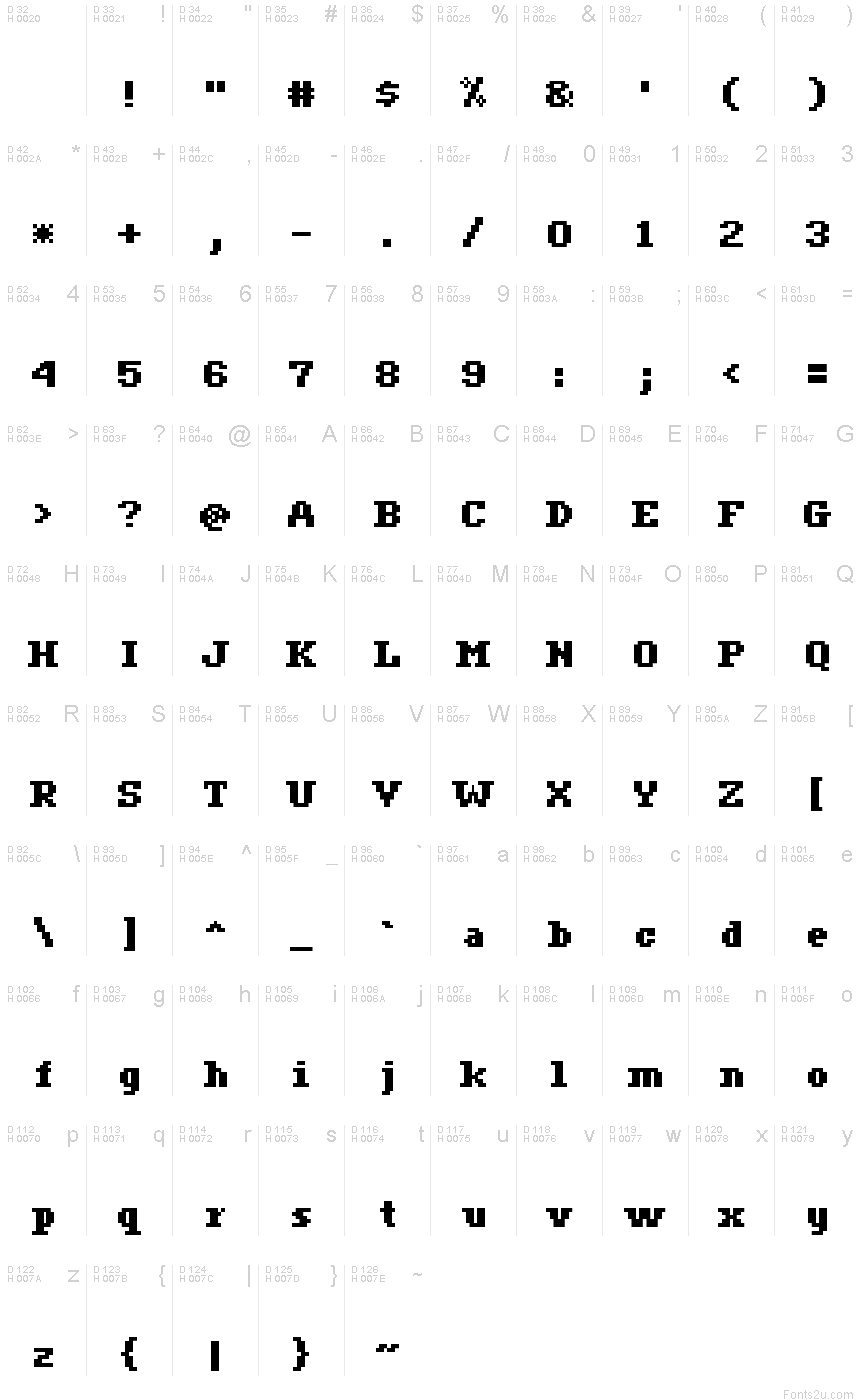
Podgląd czcionki ceriph 07_66
Ceriph 07_66 autorstwa Craiga Kroegera to darmowy szeryfowy font bitmapowy o klockowatym charakterze, nawiązującym do wczesnych ekranów. Litery łączą masywne, kwadratowe piksele z delikatnymi szeryfowymi akcentami, co sprawia, że wygląda jak coś pomiędzy fontem w niskiej rozdzielczości a tytułem retro gry.
Świetnie sprawdzi się w zinach, napisach na plakatach, brandingu inspirowanym interfejsami, oprawie graficznej albumów czy nagłówkach stron, gdzie darmowy font ma nadać całości świadomy, lo-fi sznyt. Wykorzystaj go w krótkich nagłówkach, systemach oznaczeń, planszach tytułowych lub kompaktowych logotypach, gdy zależy Ci na tym wyraźnym, siatkowym rytmie, przy jednoczesnym zachowaniu lekkiego echa tradycyjnego kroju szeryfowego.